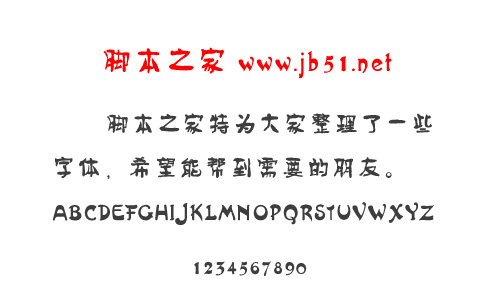
方正平和简体字体
方正平和简体字体是方正字体库中的一种字体,方正平和体因取唐代书法家孙过庭《书谱》中所倡“志气平和,不激不厉”之意而得名。这款字体的中宫宽松,笔画敦厚,并向下侧挤压,在跌宕起伏的运笔中寻求整体的平稳。方正平和体的风格夸张、放浪不羁、富有拙趣,适用于餐饮、食品、酒类品牌的广告和产品包装设计,以及影视、动漫和游戏的标题用字。 喜欢的朋友们可以前来下载使用。